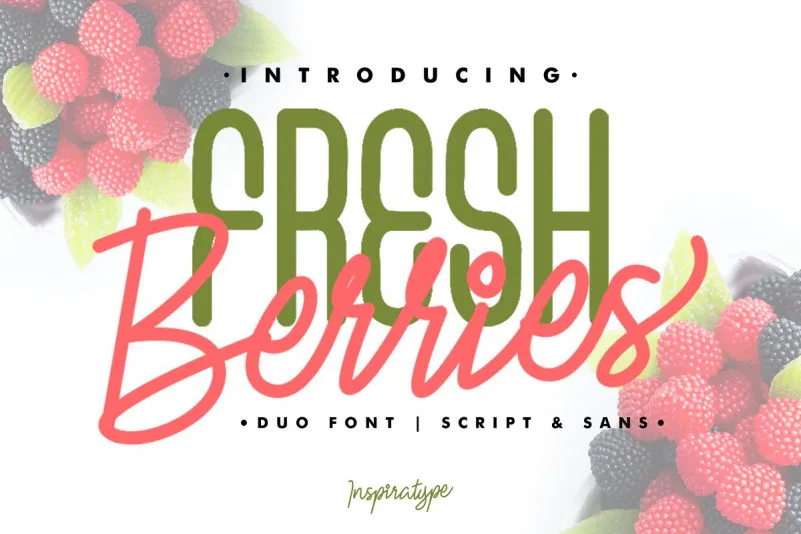
Fresh Berries Font Duo – Download Grátis
Descubra a autêntica beleza dos frutos frescos com Fresh Berries Font Duo. Este novo conjunto de fontes é uma fusão entre uma fonte círscula e uma fonte clássica, inspirada nos maiores desafios do design gráfico e nas cores vibrantes da primavera. As letras são feitas à mão, oferecendo um toque único e autêntico que reflete as sensações mais quentes e vivas. Esta dupla de fontes perfeita para qualquer projeto, seja ele uma logomarca em desenvolvimento, etiquetas customizadas ou até mesmo designs para a moda. Fresh Berries Font Duo traz suporte completo aos caracteres, incluindo alternativas do OpenType, ligaturas comuns e até mesmo swashes adicionais, permitindo que você personalize cada design de acordo com suas necessidades. Seja qual for o seu objetivo, esta fonte é certamente uma escolha atraente para tornar seus projetos ainda mais agradáveis e únicos.